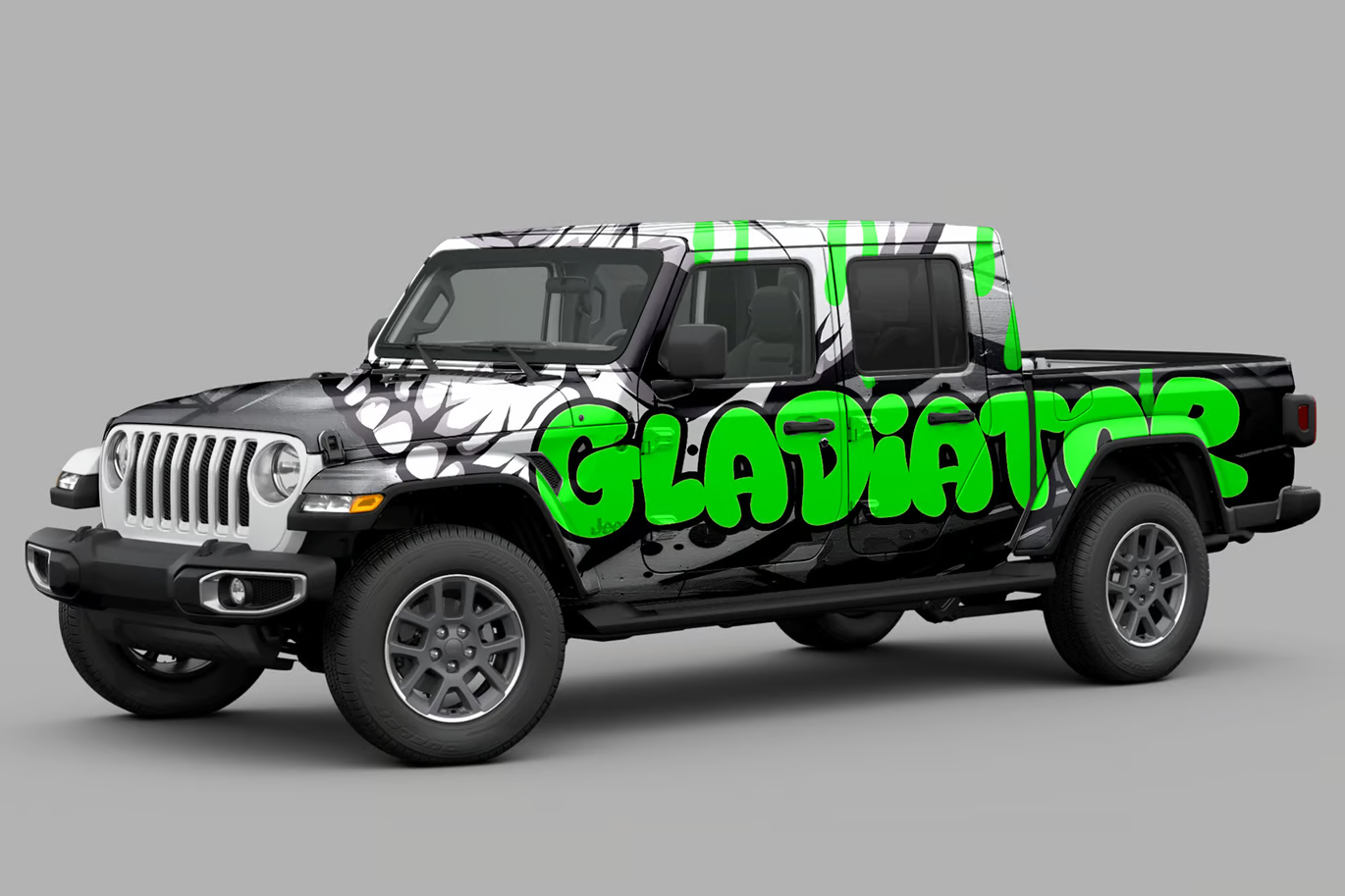
Back Wild Font
Description de Back Wild Font
Back Wild est une police de graffiti audacieuse de figuree. Cette police de graffiti est plutôt vivante, avec des swashes saillants et des courbes supplémentaires – comme un bonus dans n’importe quel design. Il présente la structure informelle et plutôt chaotique associée au mouvement street art et les ornements supplémentaires sont les éléments dynamiques du design. Qu’il s’agisse de créer des affiches, des graphiques de style urbain ou tout autre projet qui demande une énergie libre et pleine d’entrain, Back Wild transforme votre texte en un éclat plein d’entrain, ajoutant une attitude ludique à votre design.